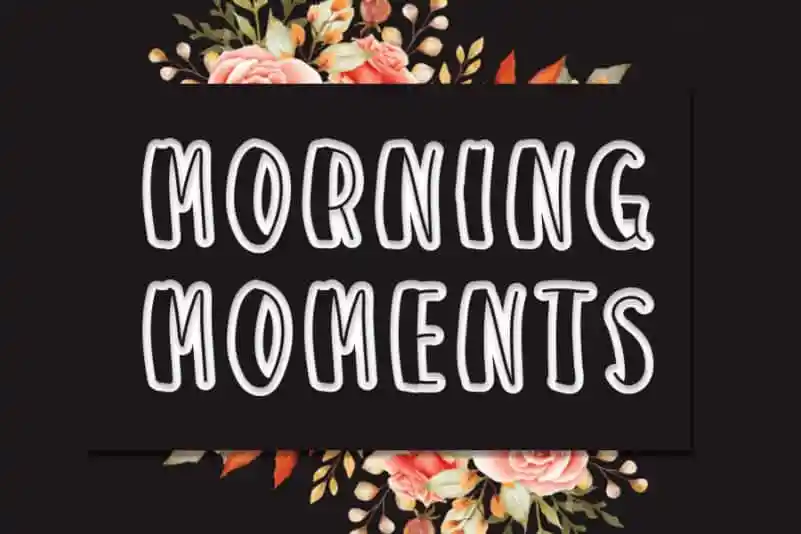
MORNING MOMENTS Display Font – Download Grátis
A Morning Moments Display Font é uma fonte criada para aqueles que buscam algo único e vibrante para seus projetos. Desenhada com a intenção de trazer um toque desconcertantemente feliz, esta fonte adicionalmente é perfeita para quem deseja dar vida aos seus ideais criativos. Sua delicadeza e originalidade fazem dela uma escolha ideal para aqueles que buscam algo inovador e encantador no design de suas próximas obras. A Morning Moments Display Font se destaca na categoria dos fontes digitais escritas a mão, com um toque acidental e quixotesco. Este é o tipo de fonte que transformará seus projetos em verdadeiros mágicos do design. Seja para uma logomarca, um título ou até mesmo o corpo da sua próxima publicação, essa fonte trará vida e destaque a qualquer projeto. Com esta fonte, você poderá explorar infinitas possibilidades criativas sem sair de casa. Adicione-a aos seus projetos e descubra como ela faz com que eles se destacuem ainda mais do resto da coleção, reforçando sua identidade visual em um mundo de design cada vez mais variado. Não espere mais – a Morning Moments Display Font é perfeita para aqueles que querem deslumbrar o público com seus trabalhos e fazer soar cada ideia como uma obra-prima original.